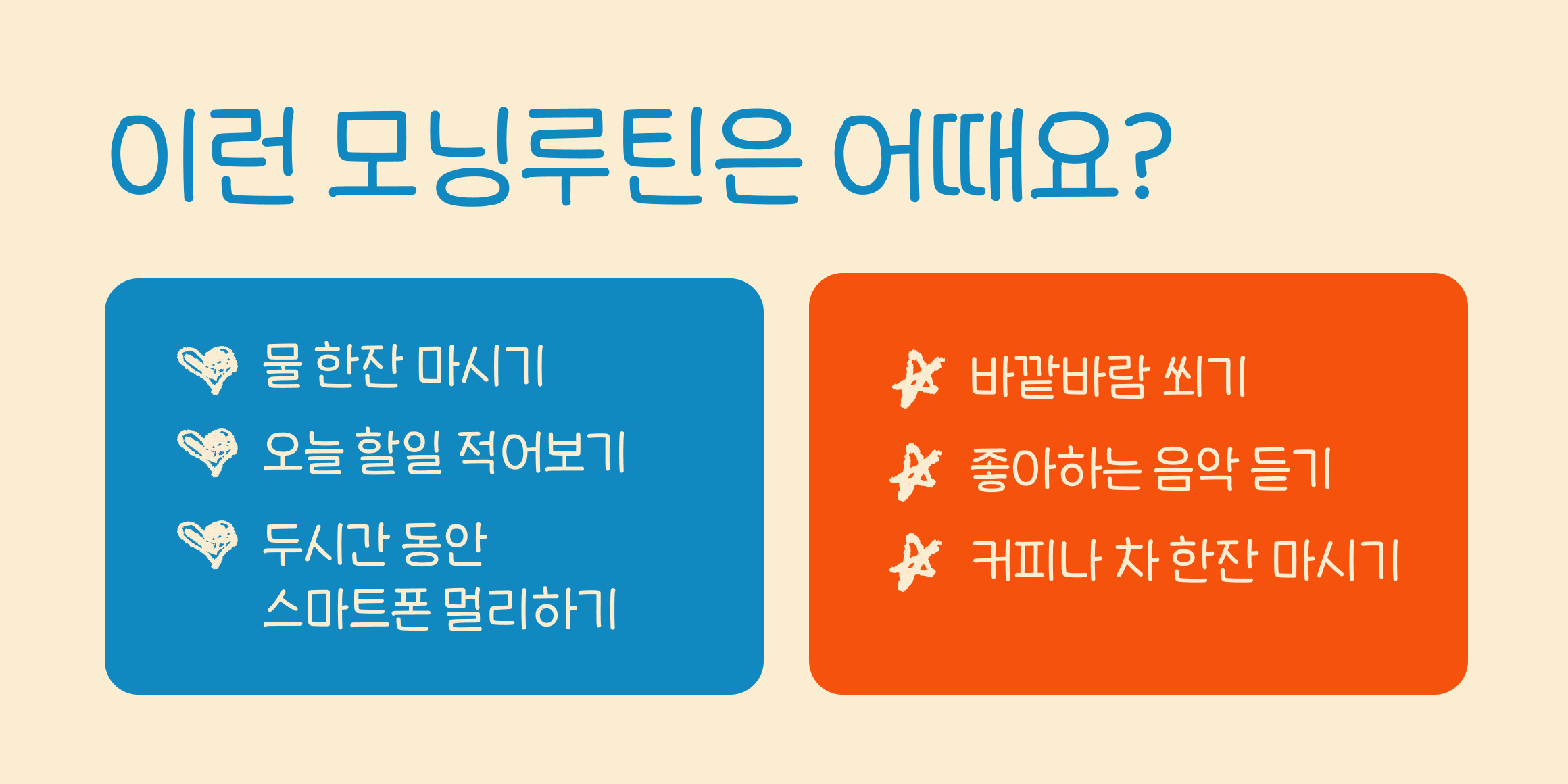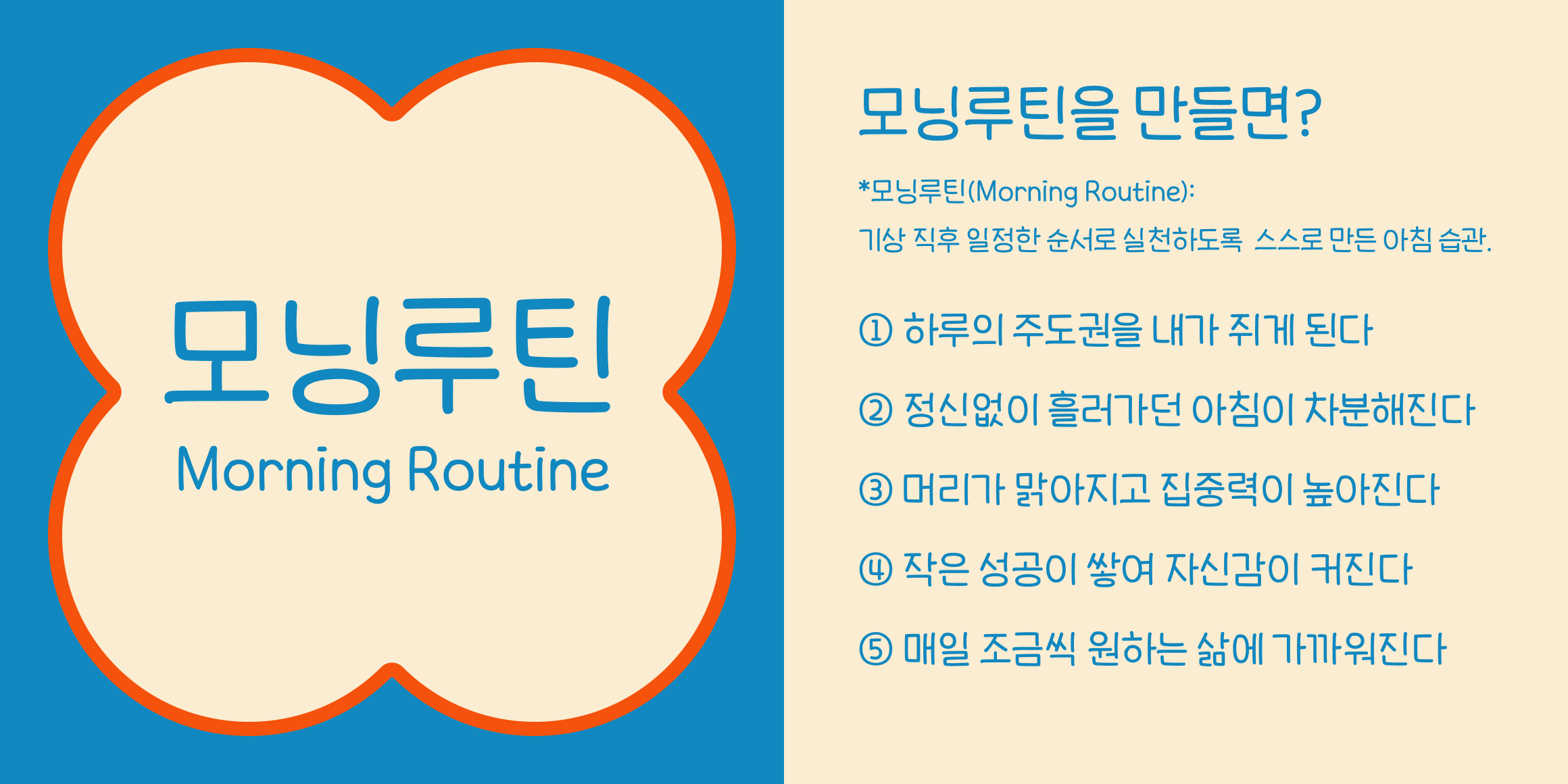
SD 모닝루틴
분류 Script,손글씨
SD 모닝루틴은 안정감 있는 꽉 찬 네모꼴에 쭉쭉 시원하게 뻗은 자소가 어우러져, 힘차게 하루를 시작하는 에너지를 담은 손글씨 폰트입니다. 한 획 한 획 또박또박 눌러쓴 듯한 필감과 안정감 있는 글줄이 특징으로, 긴 문장과 작은 크기에서도 편안한 가독성을 보여줍니다. 브이로그 영상 자막, 다이어리 등 일상을 기록하는 다양한 콘텐츠에 활용하기 좋습니다.